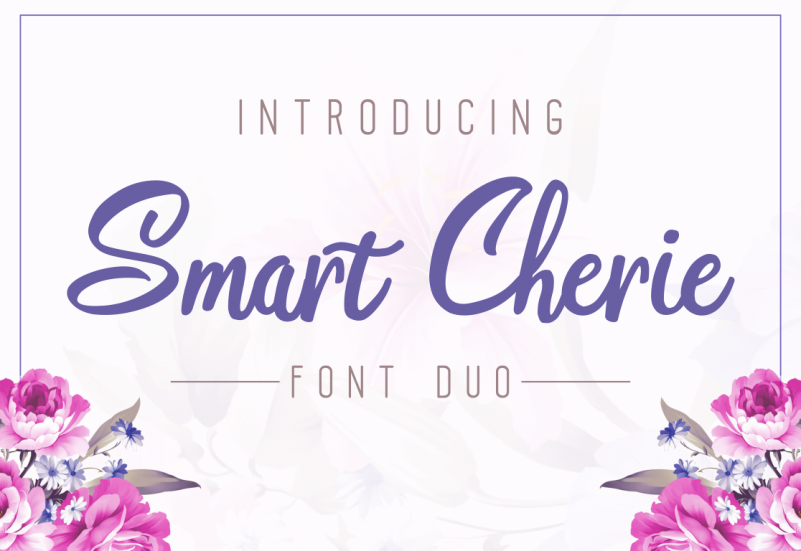
Smart Cherie Font Duo – Download Grátis
Através do ‘Smart Cherie Font Duo’, você pode conquistar a atenção com uma mistura inovadora de dois tipos de fontes únicos e charmosos. Escreva seus materiais de logomarca ou branding com um toque sutil, enquanto suas fotografias ganham vida com esta fonte sofisticada. Este par de fontes está preparado para qualquer tipo de design, seja uma invitativa criativa, uma marca digital, até mesmo em pacotes de produtos atraentes e embalagens de presentes personalizadas. Nas ocasiões especiais, como festas de casamento ou eventos únicos, o ‘Smart Cherie Font Duo’ é perfeito para deixar um toque especial ao seu material. Com uma graça única e uma aparência encantadora, você pode garantir que seus designs fiquem impressionantes em qualquer ambiente. O designer pandanwangi criou esta fonte exibindo uma mistura saborosa de charme e frescor para satisfazer todas as suas necessidades designísticas. Este par de fontes certamente dará um toque especial a seu próximo projeto gráfico, seja ele para fins pessoais ou comerciais.